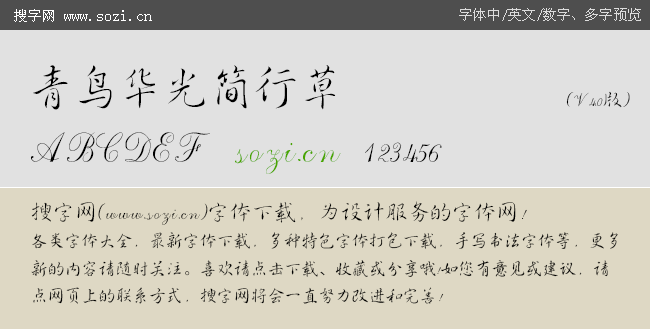
青鳥華光簡行草
搜字網(wǎng)提供一款青鳥華光簡行草中文書法字體下載,青鳥華光簡行草是一款手寫風(fēng)格的行草字體,字體書寫流暢,字形大方,整體效果十分出色,適合應(yīng)用于廣告設(shè)計、名片設(shè)計、包裝印刷、產(chǎn)品設(shè)計等應(yīng)用。
- 風(fēng)格類別: 草書